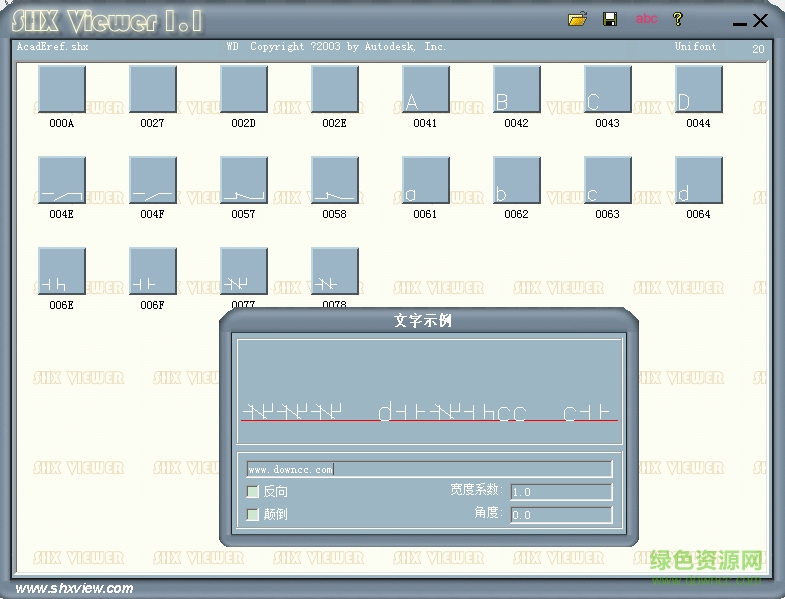
acaderef.shx什么字體?這是一款非常漂亮的cad字體,這款字體常用于cad作圖中,受到很多設(shè)計(jì)師們的青睞,喜歡這款字體的朋友歡迎來(lái)綠色資源網(wǎng)下載使用。
shx字體文件,是一種用矢量描述的形文件,shx專(zhuān)門(mén)的中文字庫(kù),這種字庫(kù)的文件擴(kuò)展名為.SHX,autocad中用戶可自己定義擴(kuò)展名為 “ .shp”形定義字體文件。
shx文件在CAD里叫形文件,它分為兩種:字體文件和符號(hào)形文件;字體文件又分兩種,可以叫做小字體和大字體。
小字體里面只包含一些單字節(jié)(在輸入法里稱(chēng)為半角)的數(shù)字、字母和符號(hào) ,在文字樣式的左側(cè)列表中列出的都是小字體文件,如果文字樣式要使用CAD字體,首先必須選擇一種小字體。
大字體是針對(duì)中文、韓文、日文等雙字節(jié)(全角)文字定制的字體文件。 在文字樣式對(duì)話框中必須勾選“ 使用大字體 ”,才能在右側(cè)列表中選擇大字體文件。由于中文、日文的字符比較多,而且每個(gè)字符的定義都比較復(fù)雜,這類(lèi)文件通常比較大,從幾百K到幾MB不等。